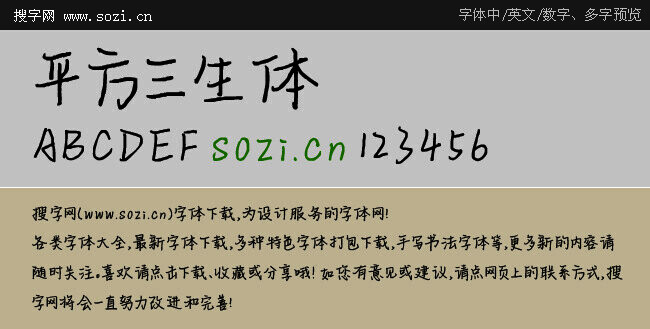
平方三生體
搜字網(wǎng)提供一款平方三生體中文書(shū)法字體下載,平方三生體是一款手寫(xiě)書(shū)法字體,字體筆觸纖細(xì),書(shū)寫(xiě)流暢自然,整體字形具有很好的視覺(jué)感。適合包裝設(shè)計(jì)、海報(bào)設(shè)計(jì)、廣告設(shè)計(jì)等應(yīng)用。
- 風(fēng)格類(lèi)別: 手寫(xiě)書(shū)法體